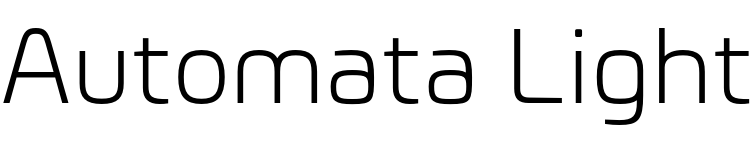
Асоціації зі шрифтом Automata LightОсобистість і характер шрифта:
лаконічний, інженерний, точний, логічний, рівний, мінімалістичний, міський, якісний, західний, спокійний, сучасний, модний, комфортний, холодний, тонкий, легкий, ясний, чистий, невагомий, прозорий, худий, гладенький, скляний, футуристичний, дротяний, автоматичний, неоновий, космічний, урбаністичний, машинний, елементарний, гнучкий
прилад, гаджет, девайс, дизайн, креслення, чистота, технології, фантастика, інновації, гра, айтішник, айті, IT, Місто, урбаністика, транспорт, космос, техніка, наука, електроніка, астрономія, небо, вода Шрифт має ознаки стилів: